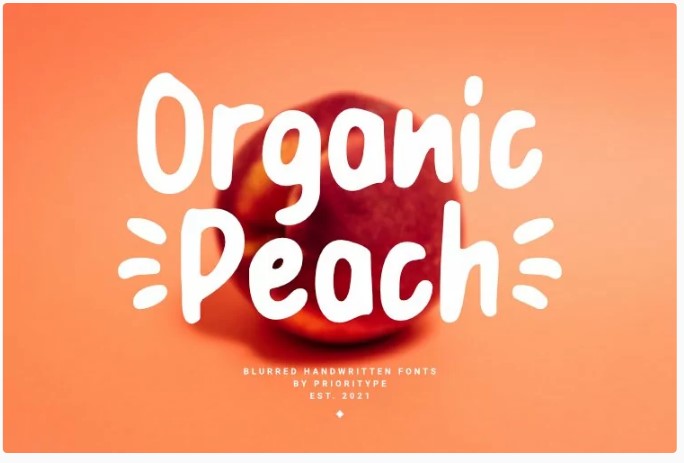
Fontbundles Organic Peach - Blurred Handwritten Fonts 2021
[Fontbundles] Organic Peach - Blurred Handwritten Fonts (2021)
Это естественный рукописный шрифт с эффектом размытия, благодаря которому шрифт выглядит гладким и простым. Подходит для использования в дизайнерских проектах, таких как цитаты, посты в социальных сетях, брендинг, товары, плакаты, обложки и многое другое, что вы можете сделать с помощью этого замечательного элемента для любого дизайна.